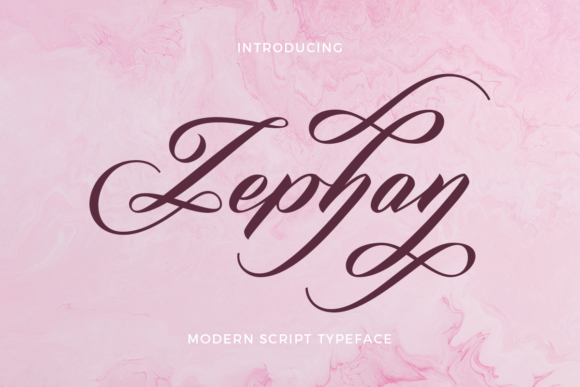
Zephan
適切なデザイン要素を見つけるのは難しい場合がありますが、Zephanは作品を即座に引き立てる優れたコレクションを提供します。
精密に作られたZephanは、クリーンなベクター、滑らかなタイポグラフィ、そして安心のための商用ライセンスを提供します。
POD(オンデマンド印刷)製品、結婚式の招待状、またはソーシャルメディアのグラフィックを作成している場合でも、Zephanは理想的です。